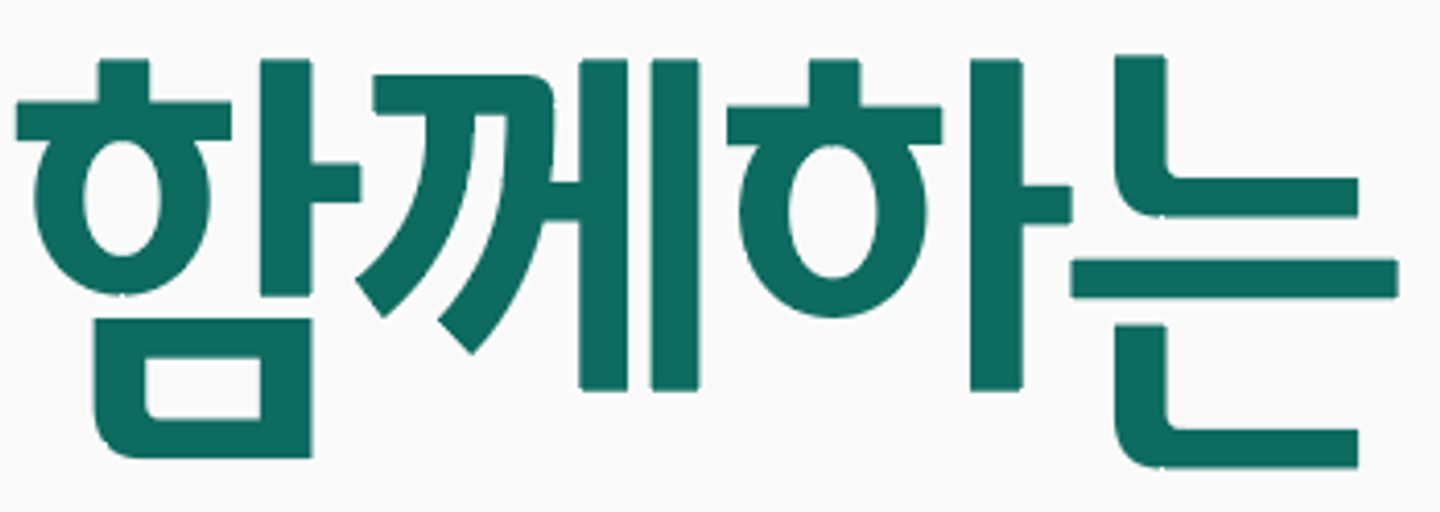
‘1973미미월드’ 폰트는 아이들의 상상력과 감성을 키워주는 종합완구 회사 ‘미미월드’와 폰트 개발사 ‘더폰트그룹’이 협업하여 완성한 폰트입니다.
미미월드 창립 45주년을 기념하여 제작되었으며, 2018년 7월, 창립기념일을 맞이하여 모든 분들이 자유롭게 사용하실 수 있도록 무료로 배포합니다.